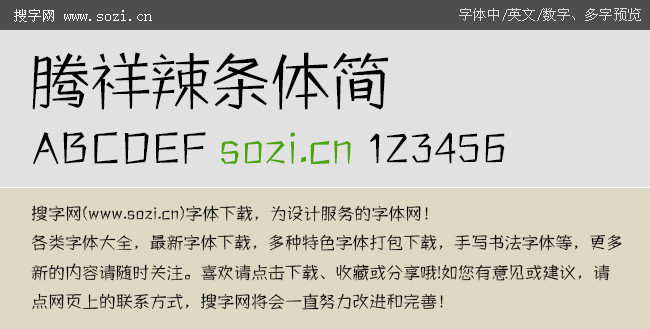
騰祥辣條體簡(jiǎn)
搜字網(wǎng)提供一款騰祥辣條體簡(jiǎn)中文字體下載, 騰祥辣條體簡(jiǎn)是一款十分不錯(cuò)的中文美術(shù)字體,該字體筆畫銳意簡(jiǎn)約,靈動(dòng)多變、整幅字充滿稚趣童真又勁道十足,能夠適用于藝術(shù)設(shè)計(jì)、包裝印刷、簽名設(shè)計(jì)、圖形設(shè)計(jì)等領(lǐng)域。(此款為個(gè)人非商用版,如需商用請(qǐng)聯(lián)系騰祥字庫(kù)購(gòu)買)